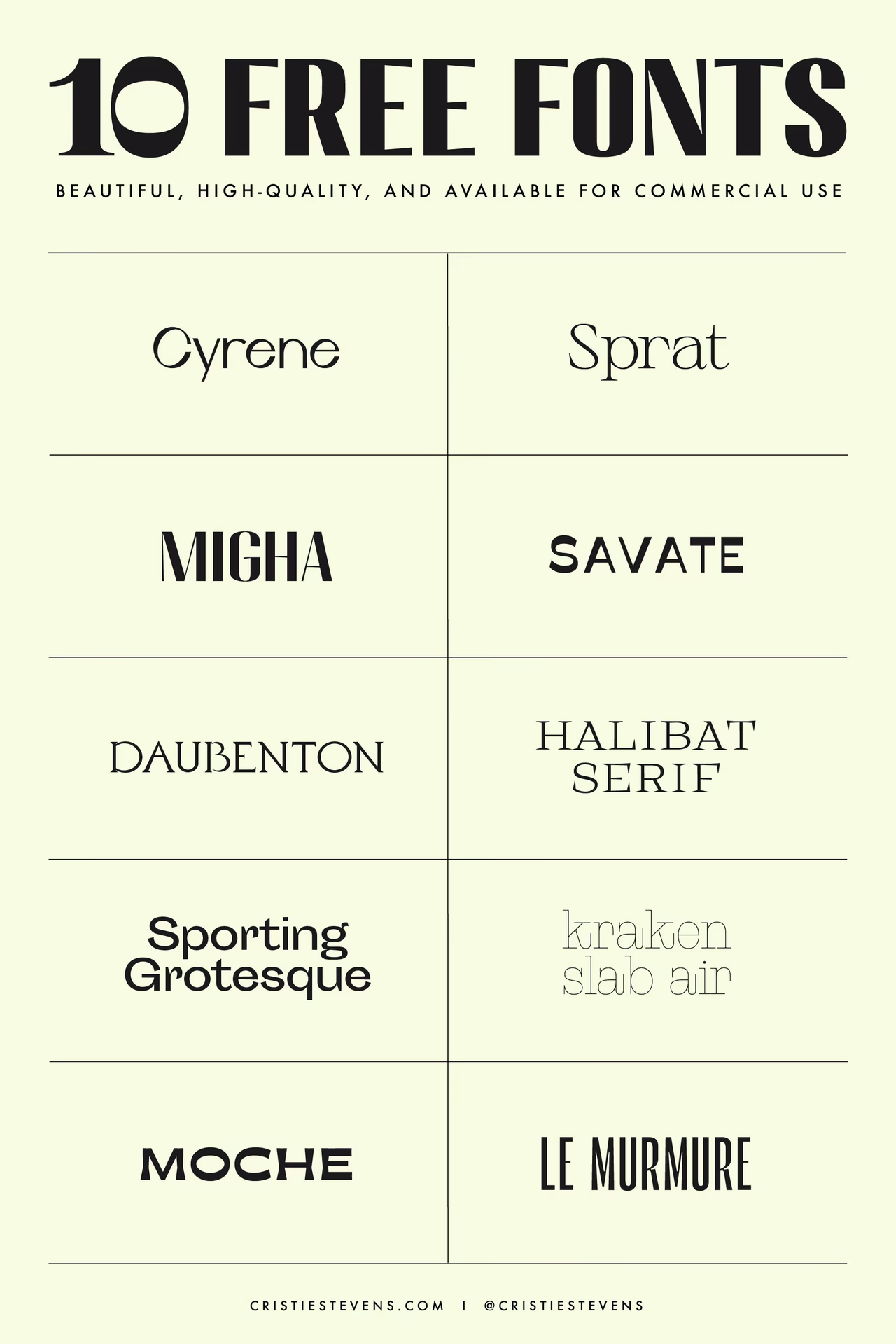
Gratis Serif Skrifttyper til Kommerciel Brug
Serif-skrifttyper er kendetegnet ved de små 'fødder' eller strøg (seriffer) i enden af bogstavets streger. De forbindes ofte med tradition, pålidelighed og elegance og bruges hyppigt i bøger, aviser og til overskrifter. Der findes mange fremragende serif-skrifttyper, der er tilgængelige gratis til kommerciel brug. Her er en liste over nogle eksempler, som er nævnt som værende gratis til kommerciel brug:
- Arrow
- RM Almanac
- Chanticleer Roman NF Regular
- Dustismo Roman Bold
- Bona Nova
- Alegreya
- Amethysta Regular
- Old Standard TT
Disse skrifttyper repræsenterer forskellige stilarter inden for serif-kategorien, fra klassiske og tidløse udtryk til mere moderne fortolkninger. At have adgang til sådanne kvalitetsskrifttyper uden omkostninger åbner op for mange designmuligheder i kommercielle projekter.
Er Adobe Fonts Gratis til Kommerciel Brug?
Et ofte stillet spørgsmål er, om skrifttyperne, der følger med et Adobe Creative Cloud-abonnement (kendt som Adobe Fonts, tidligere Typekit), må bruges kommercielt. Svaret er et klart ja, forudsat at du har et aktivt og gyldigt abonnement, der inkluderer adgang til Adobe Fonts.
Adobe's standard skrifttype-licensaftale (EULA - End User License Agreement) tillader både personlig og kommerciel brug af skrifttype-softwaren til at skabe designs og dokumenter. Dette omfatter en bred vifte af anvendelser:
- Trykte materialer: Bøger, magasiner, brochurer, emballage, tøj osv.
- Logoer og branding: Brug i firmalogoer og anden visuel identitet.
- Renderet indhold: Brug i billeder (f.eks. i Photoshop), film, video og bitmap-grafik, hvor teksten er en del af billedet/videoen og ikke kan redigeres som levende tekst af slutbrugeren.
Den primære begrænsning ligger i *distributionen* af selve skrifttype-softwaren. Du må ikke give skrifttype-filen (f.eks. .otf, .ttf, .woff) direkte til din kunde eller andre, medmindre de selv har en gyldig licens (f.eks. via deres eget Adobe-abonnement). I stedet skal du sikre, at designet, du leverer, ikke indeholder den originale skrifttype som en separat, redigerbar fil. Dette kan gøres ved at:
- Konvertere teksten til vektoromrids (outlines) i programmer som Adobe Illustrator eller InDesign.
- Rasterisere teksten (gøre den til en del af et billede) i programmer som Adobe Photoshop.
- indlejre skrifttypen i et elektronisk dokument som en PDF eller e-bog, hvor skrifttypen er subsetted (kun de nødvendige tegn er inkluderet) og sikret mod udtrækning eller redigering af slutbrugeren.
Så længe det endelige produkt, du leverer til din kunde eller distribuerer, ikke gør det muligt for modtageren at installere eller redigere teksten med den originale skrifttype-fil, er du på den sikre side med Adobe Fonts' kommercielle licens.
Hvordan Tjekker Man en Skrifttypes Licens?
Den vigtigste lektie, når det kommer til gratis skrifttyper til kommerciel brug, er at altid tjekke licensen. Antag aldrig, at en skrifttype er gratis til kommerciel brug, bare fordi du fandt den på en 'gratis skrifttype'-hjemmeside.
Her er, hvordan du typisk finder licensinformationen:
- Downloadpakken: Når du downloader en skrifttype, medfølger der ofte en tekstfil (.txt) eller en PDF-fil med licensbetingelserne. Filen kan hedde noget i retning af 'LICENSE.txt', 'README.txt' eller bære navnet på skrifttypen efterfulgt af 'License'. Åbn og læs denne fil grundigt.
- Hjemmesiden: Informationen om licensen findes ofte på den hjemmeside, hvor du downloader skrifttypen fra. Se efter afsnit som 'Licensing', 'Terms of Use', 'About This Font' eller lignende. Mange sider, især Google Fonts og Font Squirrel, gør det meget klart, hvilken type licens der gælder, ofte med ikoner eller tydelige markeringer.
- Søgning: Hvis du er i tvivl, kan du søge på navnet på skrifttypen plus ordene 'license' eller 'commercial use'. Dette kan føre dig til den oprindelige kilde eller en forklaring på licensen.
Vær opmærksom på forskellige typer af licenser. SIL Open Font License (OFL) er en almindelig open source-licens, der typisk tillader brug, ændring og distribution af skrifttypen (under visse betingelser, herunder at man ikke sælger skrifttypen i sig selv). Andre licenser kan have flere begrænsninger. Det er dit ansvar som designer at forstå og overholde disse betingelser.
Faldgruber og Ting at Undgå
Selvom gratis kommercielle skrifttyper er fantastiske, er der et par faldgruber, du bør være opmærksom på:
- Manglende Licensinformation: Hvis du ikke kan finde klar licensinformation for en skrifttype, er det sikreste at antage, at den *ikke* er gratis til kommerciel brug, eller helt undlade at bruge den i kommercielle projekter.
- "Donationware" eller "Shareware": Nogle skrifttyper beder om en donation eller er gratis til testbrug, men kræver betaling for fuld kommerciel brug. Læs licensen for at afgøre dette.
- Downloads fra Usikre Kilder: Undgå at downloade skrifttyper fra mistænkelige hjemmesider. De kan indeholde virus eller tilbyde skrifttyper ulovligt. Hold dig til anerkendte platforme.
- Ændring af Skrifttypen: Hvis du planlægger at ændre i selve skrifttypefilen (f.eks. justere formerne på bogstaverne), skal du sikre dig, at licensen tillader 'modification' eller 'derivative works'. Mange gratis kommercielle licenser tillader dette, men ikke alle.
Ved at være omhyggelig med at tjekke licenserne kan du trygt og lovligt bruge gratis skrifttyper i alle dine kommercielle bestræbelser.
Spørgsmål og Svar om Gratis Kommercielle Skrifttyper
Her er svar på nogle hyppige spørgsmål vedrørende brug af gratis skrifttyper kommercielt:
Må jeg bruge en gratis kommerciel skrifttype i et logo?
Ja, generelt tillader licenser for 'gratis til kommerciel brug' netop dette. Et logo er en almindelig form for kommerciel anvendelse.
Hvad hvis jeg bruger en skrifttype kun til personlig brug i et kommercielt projekt ved en fejl?
Dette er et licensbrud og kan potentielt føre til juridiske problemer, herunder krav om betaling af licensafgifter eller erstatning. Det er derfor, det er så vigtigt at dobbelttjekke licensen.
Skal jeg nævne skrifttypens designer eller kilde, når jeg bruger en gratis kommerciel skrifttype?
Dette afhænger af den specifikke licens. Nogle licenser (f.eks. OFL) kræver, at du inkluderer den originale licensfil med din distribution af skrifttypen, men kræver typisk ikke kreditering i selve designet. Tjek licensdokumentet for at være sikker.
Kan jeg sælge et design (f.eks. en T-shirt) der bruger en gratis kommerciel skrifttype?
Ja, hvis skrifttypen er licenseret til kommerciel brug, må du bruge den i produkter, du sælger, som f.eks. T-shirts, plakater, kopper osv., hvor skrifttypen er en del af designet på produktet.
Kan jeg indlejre en gratis kommerciel skrifttype på et website?
Ja, de fleste gratis kommercielle licenser, især dem fra kilder som Google Fonts, er specifikt designet til dette formål. Dette kaldes ofte '@font-face' indlejring.
Afsluttende Tanker
Verdenen af gratis skrifttyper til kommerciel brug er rig og mangfoldig og tilbyder utallige muligheder for designere på alle niveauer. Fra klassiske serif-skrifter, der formidler troværdighed, til moderne sans-serifs, der signalerer innovation, er der en gratis skrifttype derude til næsten ethvert tænkeligt projekt. Adobe Creative Cloud-abonnenter har yderligere adgang til et stort bibliotek af skrifttyper, der også kan bruges kommercielt under de angivne betingelser.